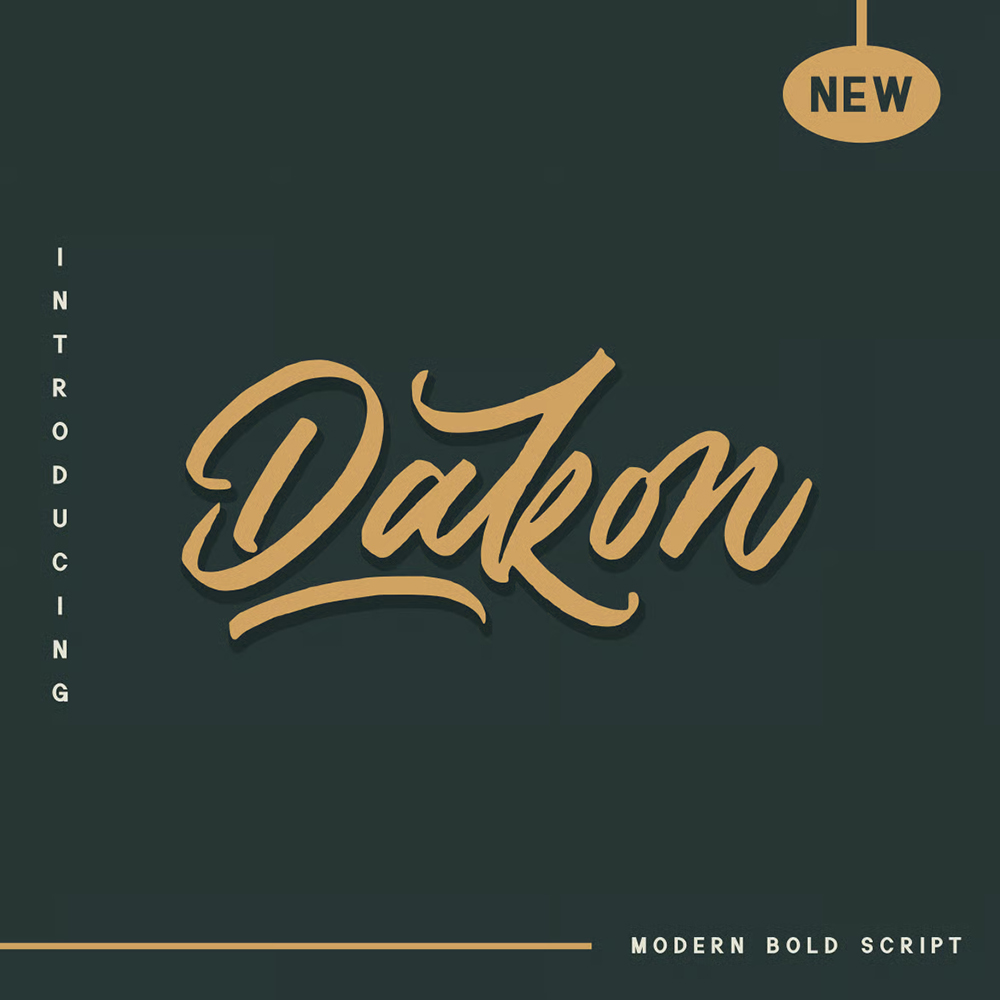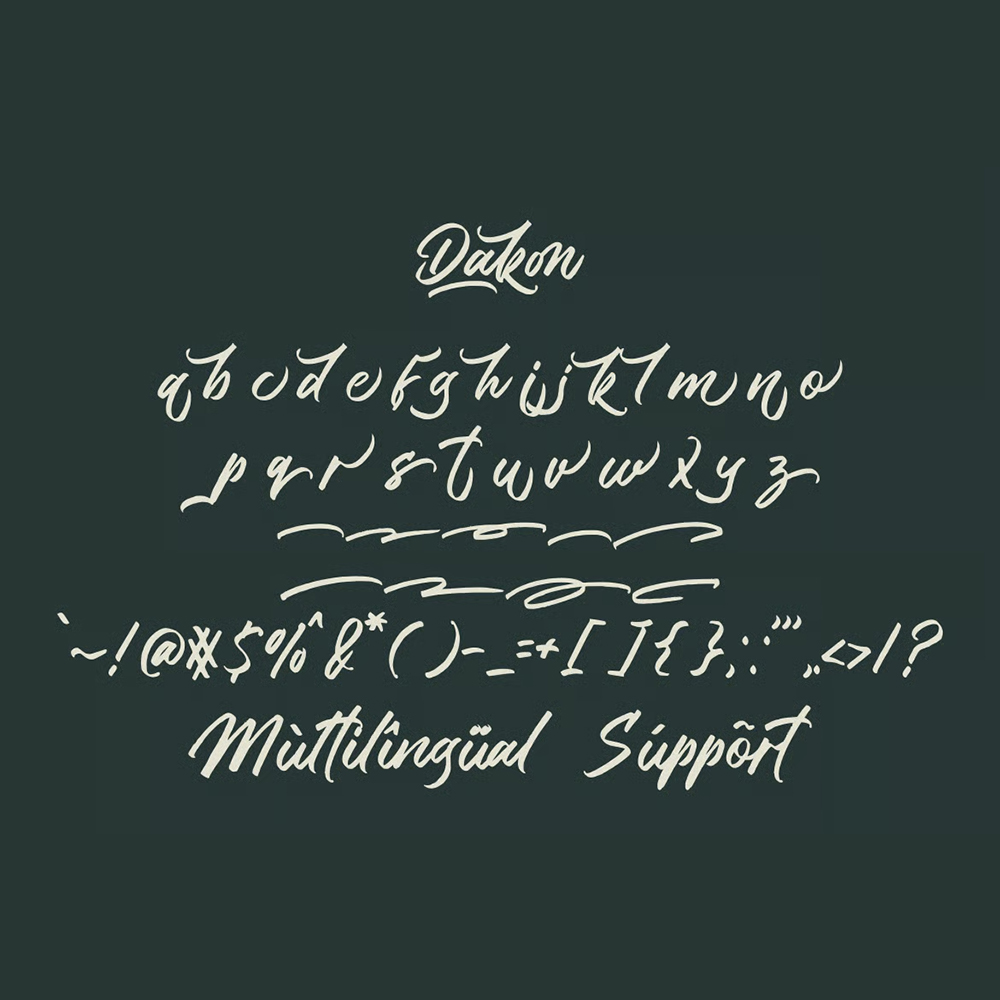
فونت پرمیوم و انگلیسی Dakon Font یک فونت مدرن با فونت Rapi است که ظاهری زیبا دارد و برای پشتیبانی از انواع طرحها و کسب و کار شما مناسب است. فونتی عالی و مناسب برای لوگو و برندسازی، عکاسی، دعوتنامهها، واترمارکها، تبلیغات، طراحی محصولات، لوازم التحریر، طراحی عروسی، برچسبها، بستهبندی محصول، رویدادهای ویژه یا هر چیز دیگری که نیاز به محتوای پررنگ دارد.